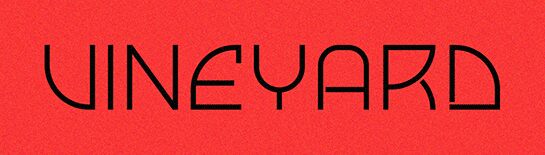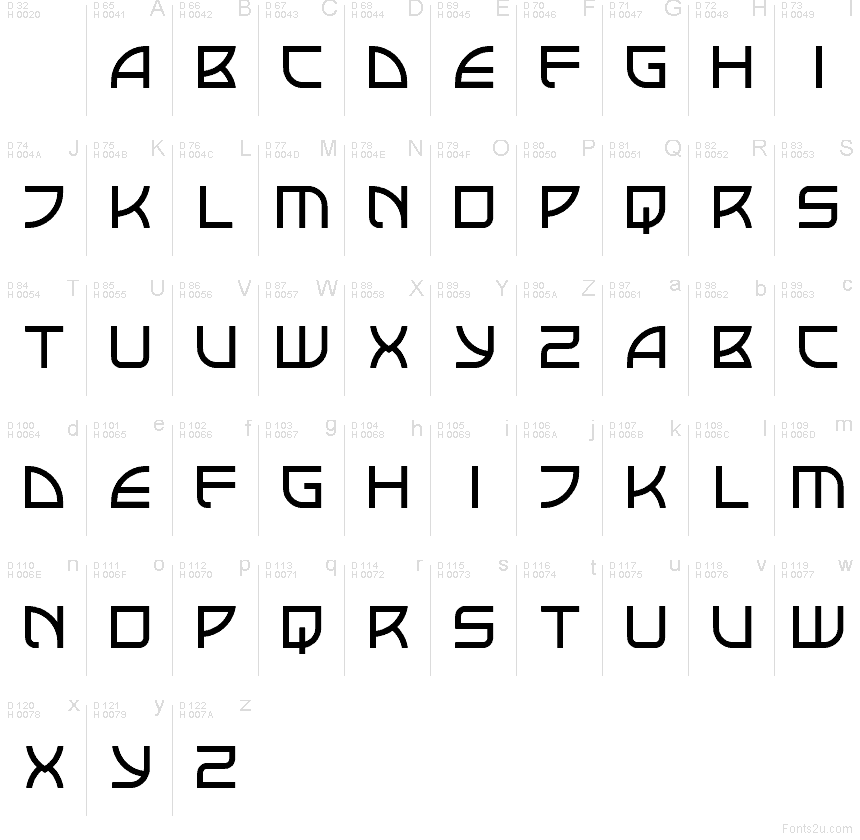
Vineyard Beograd de Vladimir Nikolic es una tipografía display futurista y gratuita, construida con trazos geométricos anchos y curvas rigurosamente controladas. Sus letras tienen un carácter arquitectónico y un marcado estilo retrotecno.
Una marca de tecnología, un sello de música electrónica o un espacio moderno podrían utilizar sus formas geométricas abiertas para logotipos, envases y carteles de eventos, especialmente cuando una estética elegante de la era de las máquinas encaja con el tema. El diseño atraerá sobre todo al público afín a los gráficos de la era espacial, la cultura de club experimental y la geometría limpia de la electrónica de finales del siglo XX.